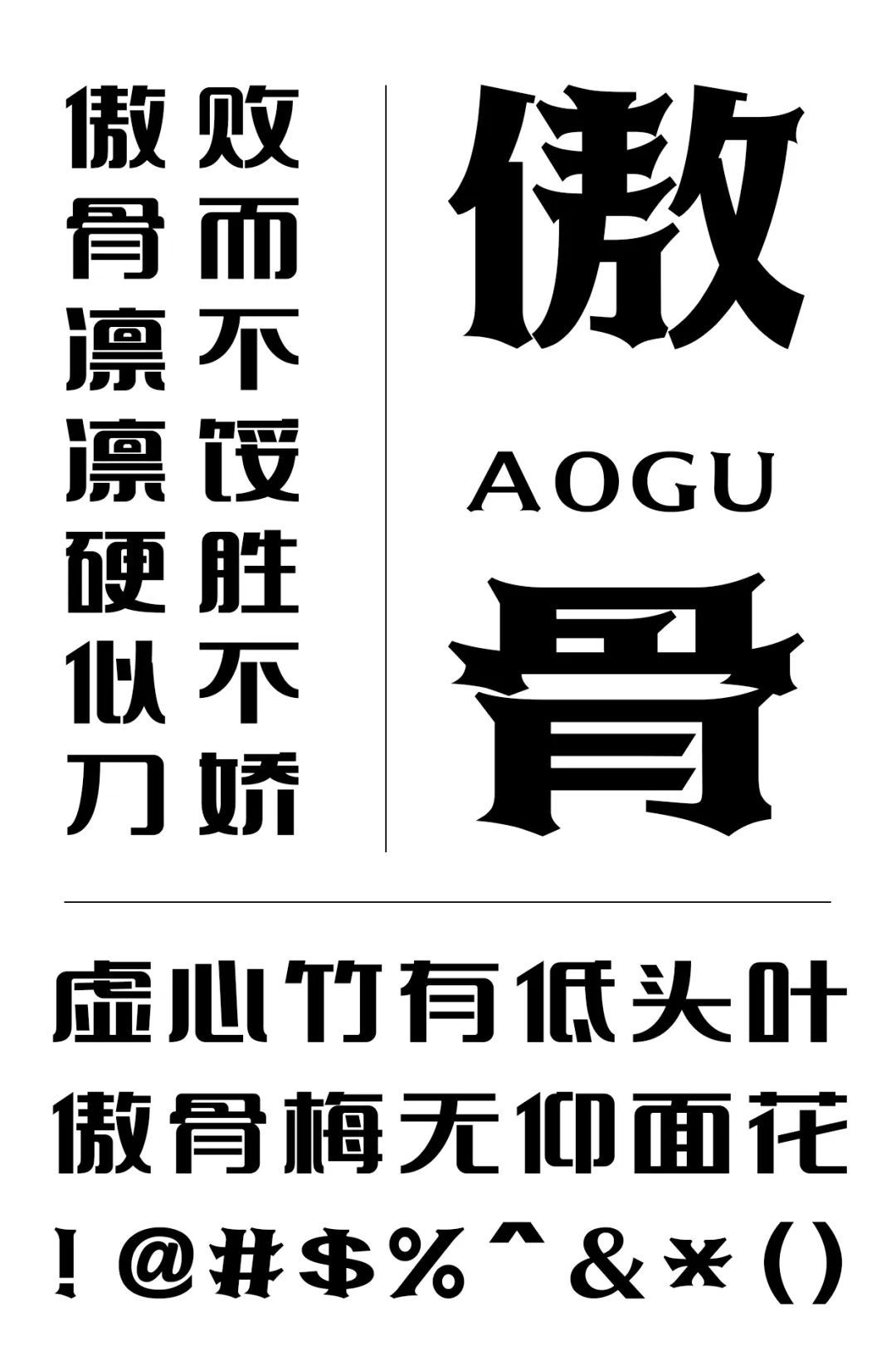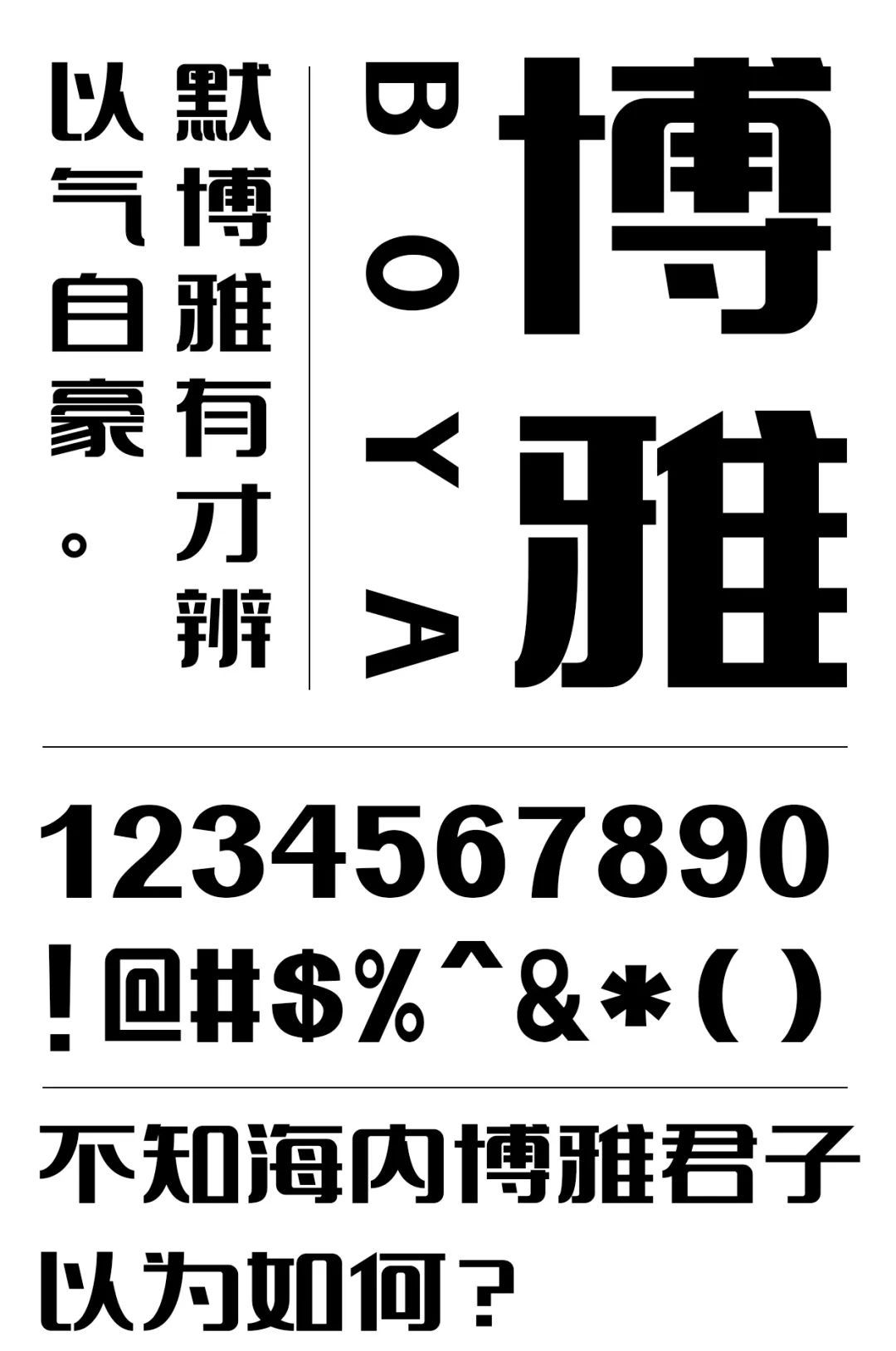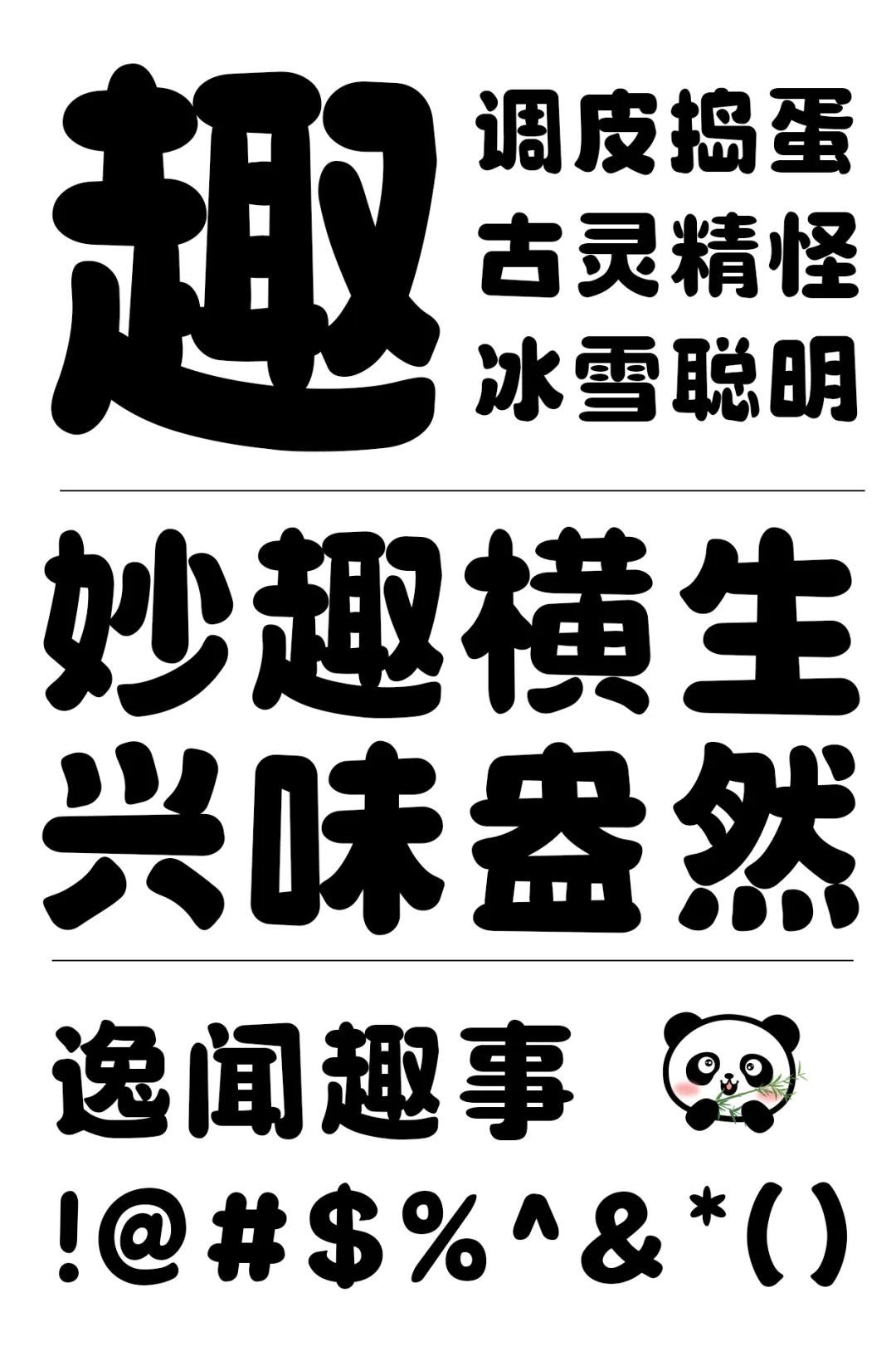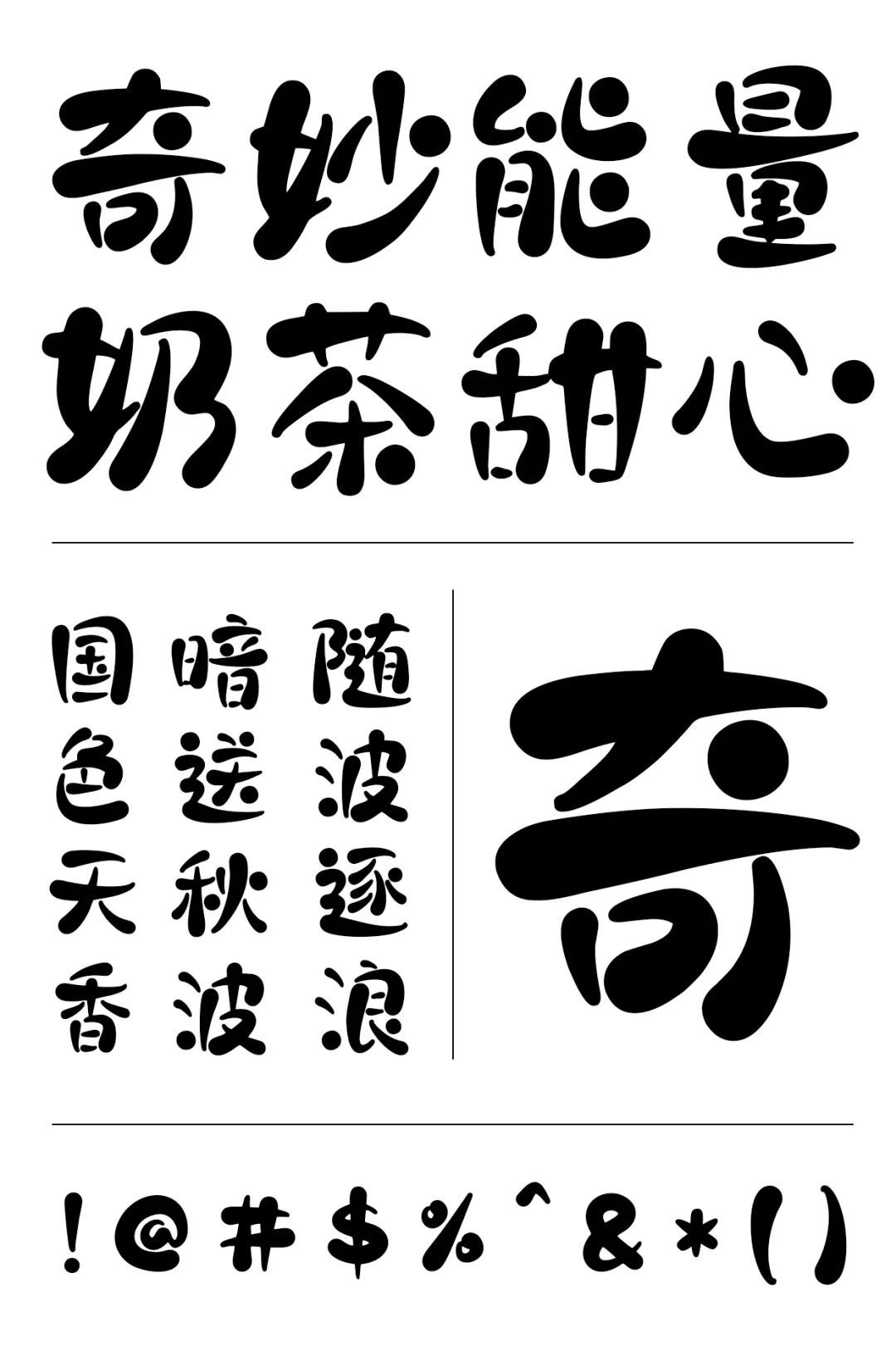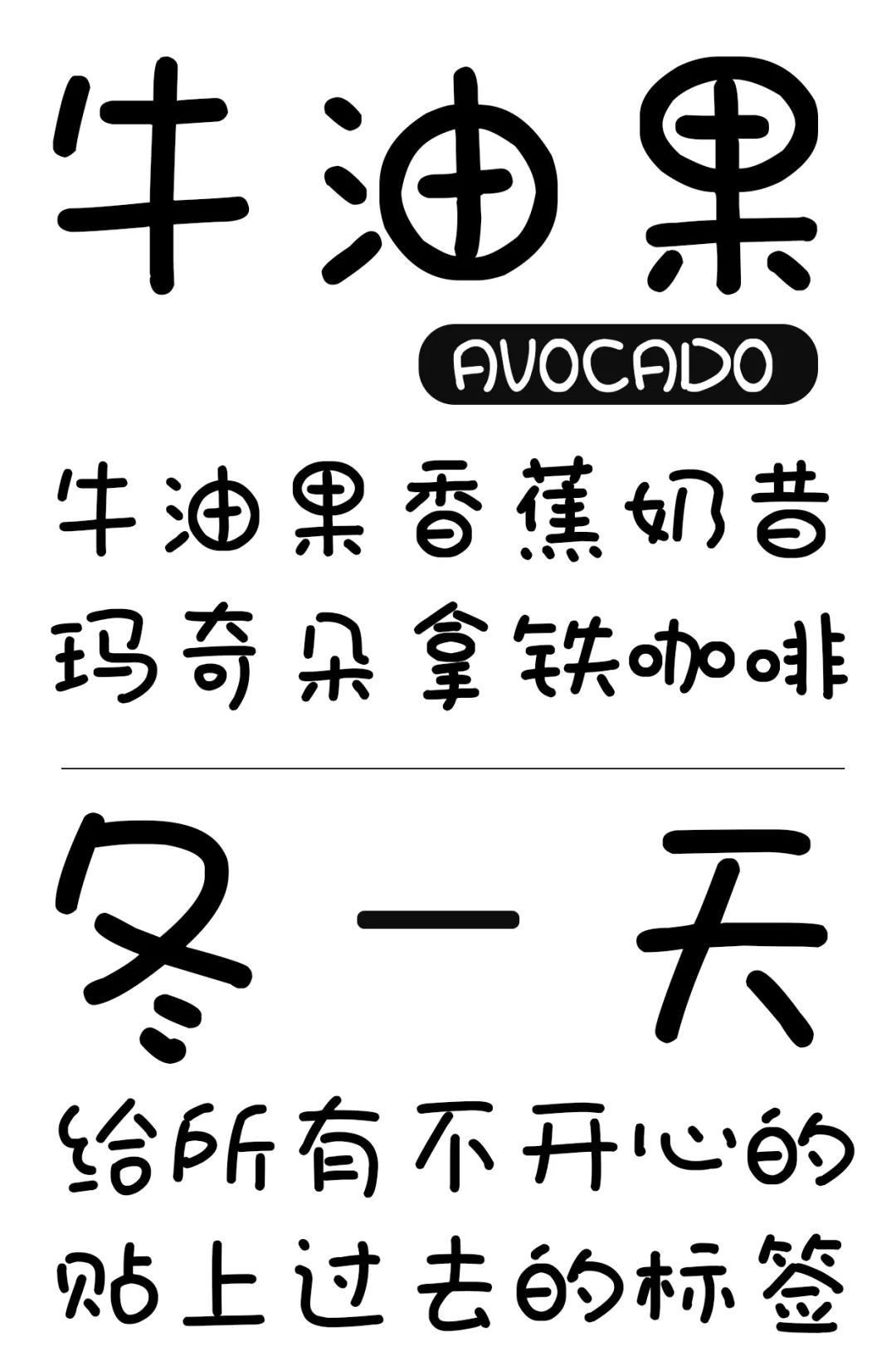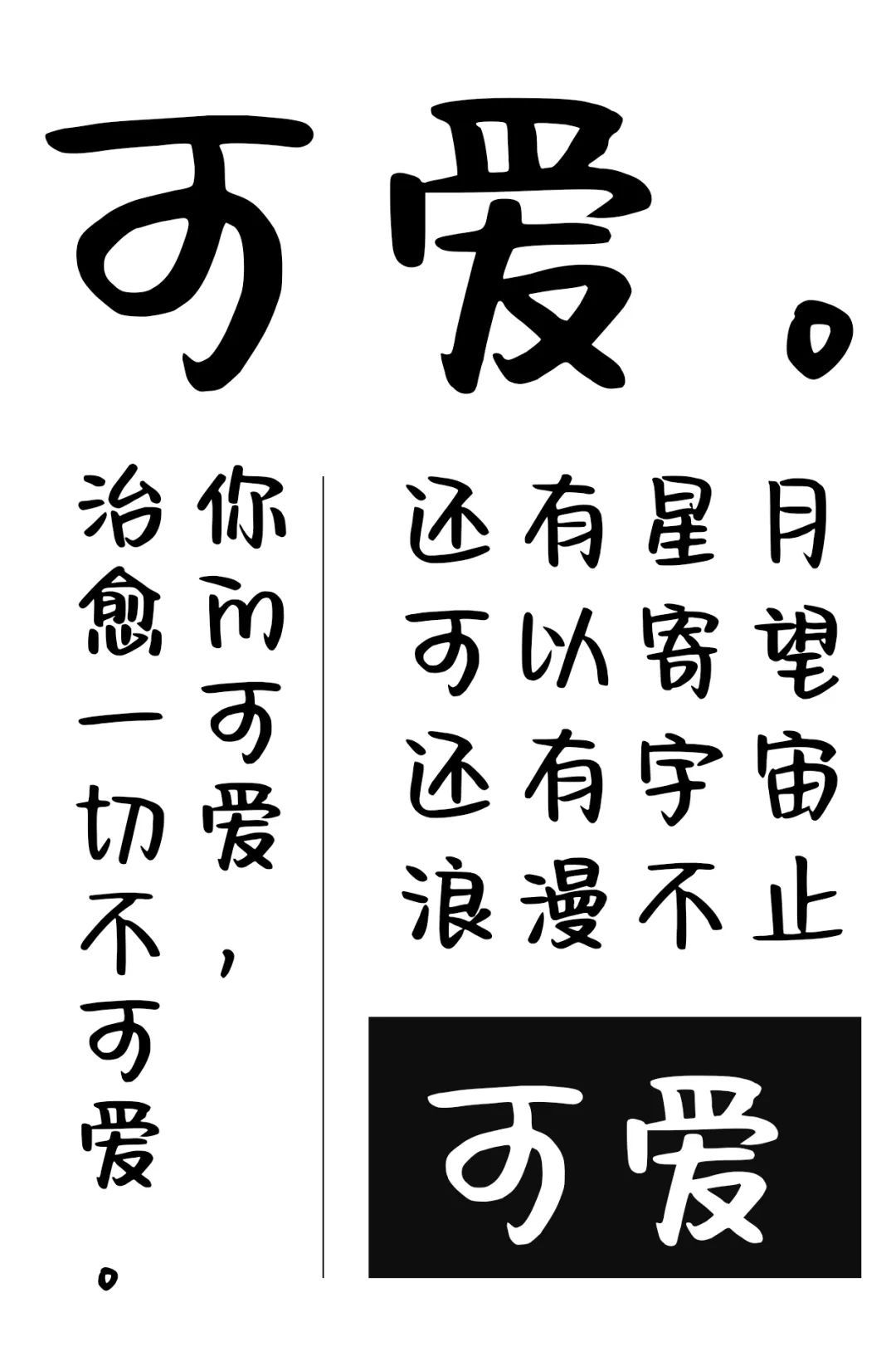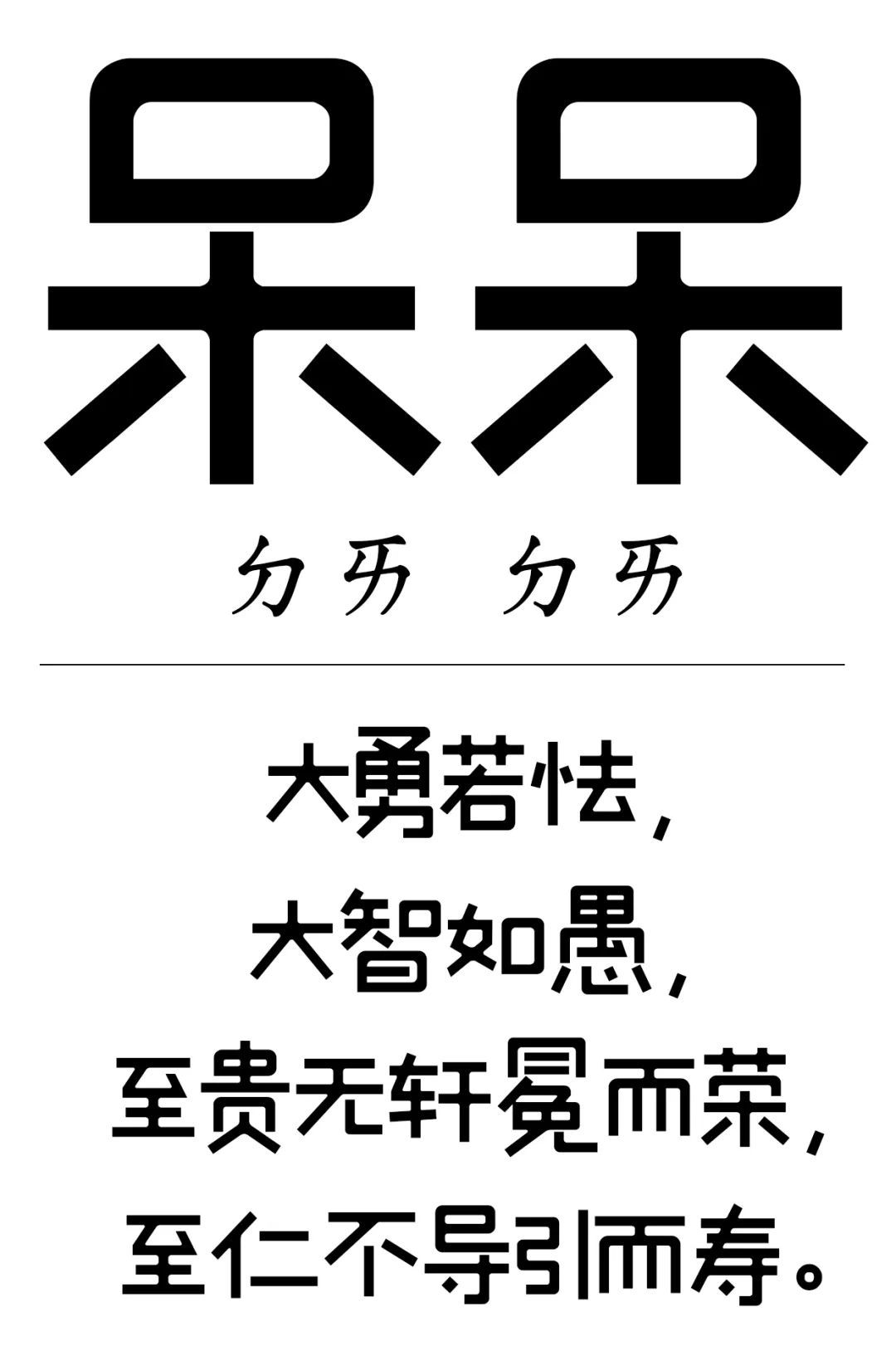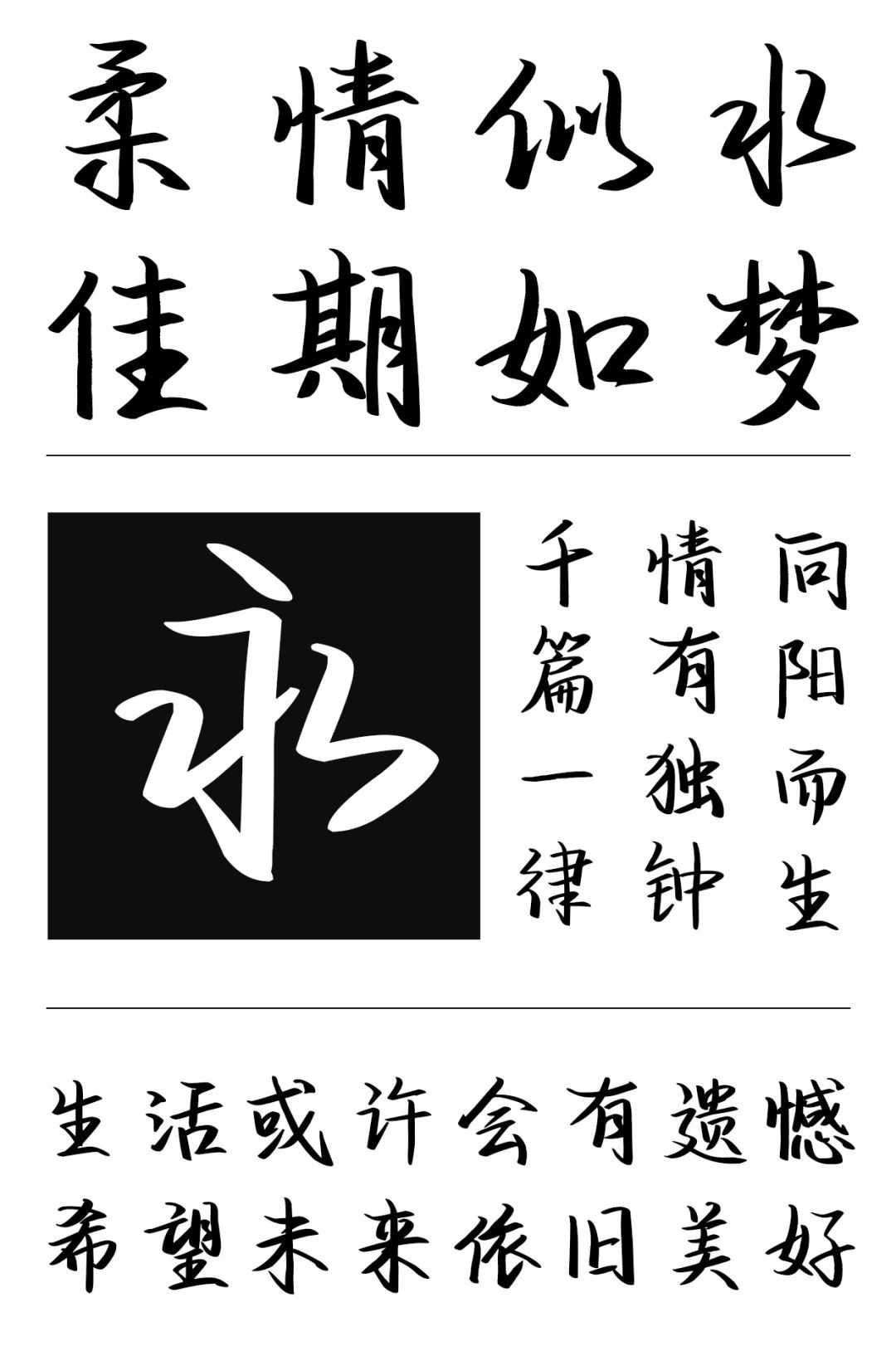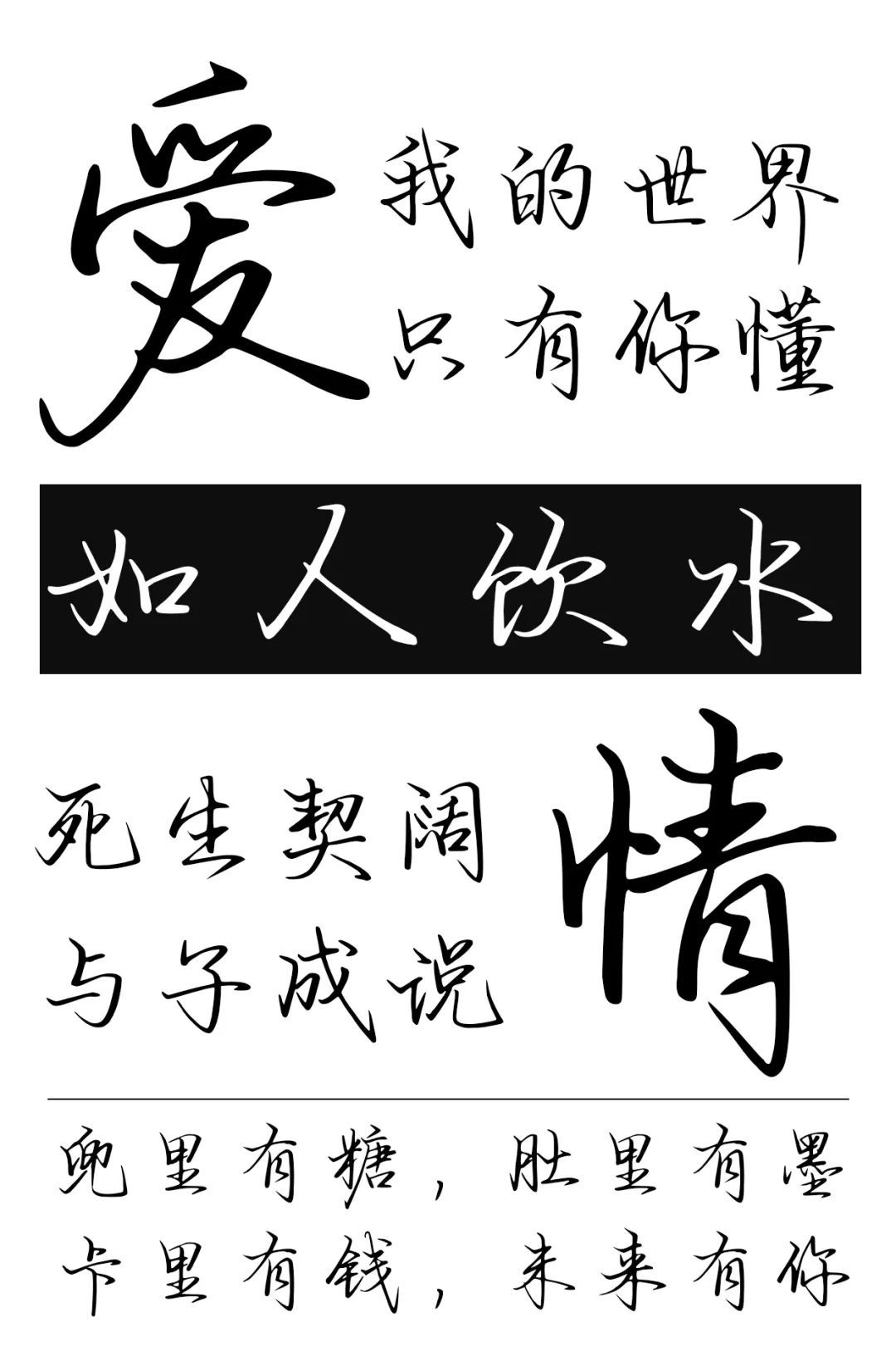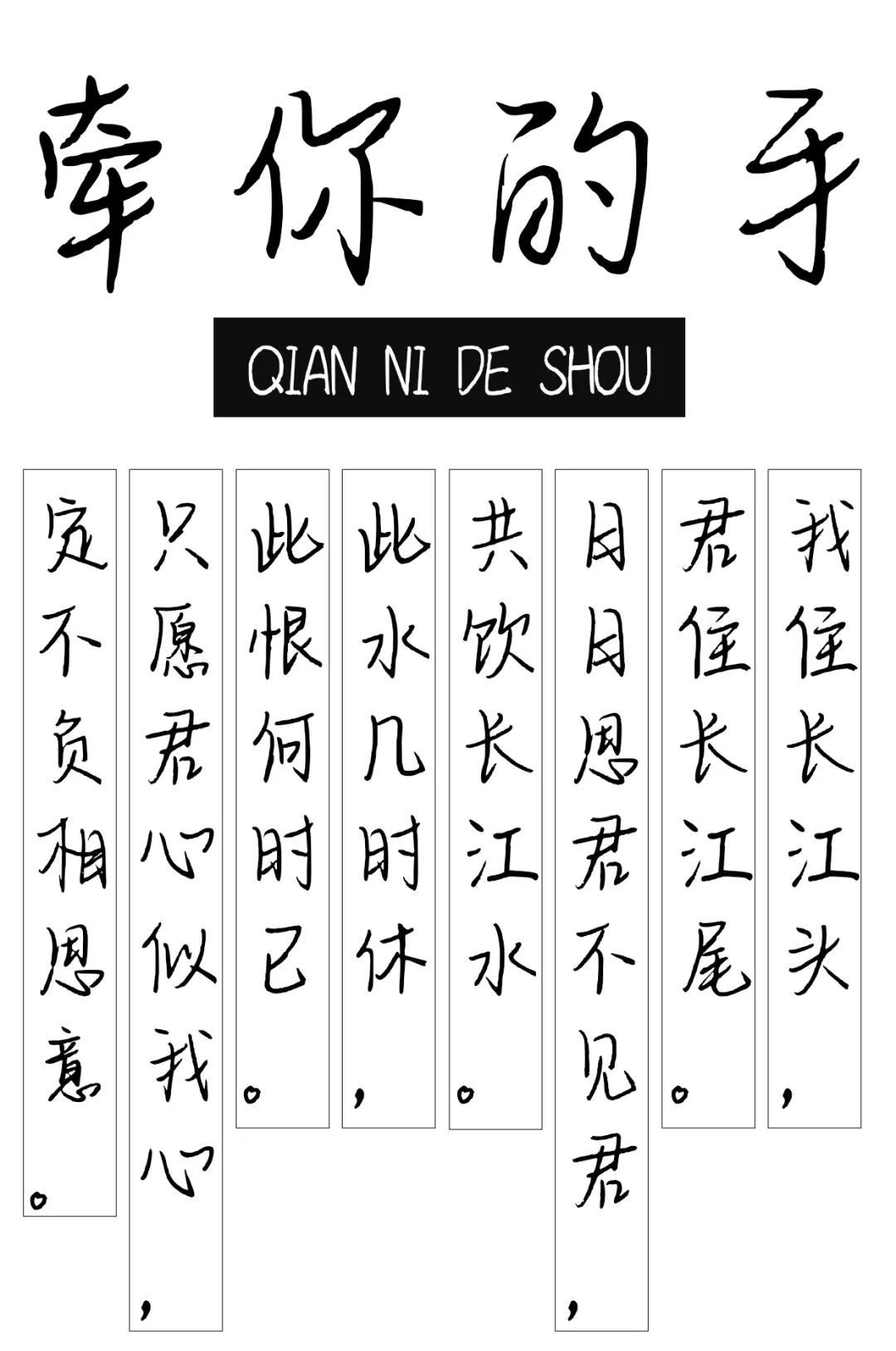
1、上首傲骨体
硬朗的线条之间的粗细变化不一,更显字形轮廓感。字体整体风格颇有文人傲骨风范。
2、上首博雅体
上首博雅体,字体笔画端正。博雅顾名思义笔画大气字体端正富有内涵,结字方正,气息儒雅,整体风格博学大气。
3、萌趣体
萌趣体这款字能在趣味、活泼、可爱、萌趣中体现,粗黑为字形基础,不规则的笔画,在排版时能表现趣味的节奏感。
4、上首波波手写体
上首波波手写体,以一端粗一端细的圆润的笔画和圆点书写,笔画整体浑圆,柔和、可爱,像果冻,像水滴,像中文感叹号,给人以温柔、俏皮、波动,胖乎乎、萌萌哒的感觉。
5、牛油果味的冬天
牛油果味的冬天,粗细的笔画加上圆体的设计风格,可爱又非稚嫩的气质凸显而出。
6、可爱的软糖奶酪
可爱的软糖奶酪这款字体富有意趣的笔画,简单清晰的结构,可爱的气质拿捏的恰到好处十分适合软萌妹子,萌萌哒的奶酪体让你每天都有萌萌的心情。
7、上首呆呆体
上首呆呆体,字体笔画均匀,横竖粗细一致,字型圆润,具有卡通动漫的风格。
8、千篇一律的温柔
千篇一律的温柔这是一款十分飘逸清新的字体,笔画给人舒适的感觉,没有尖酸刻薄的锐气,只有生动活泼的朝气。
9、听晚风将爱情吹散
听晚风将爱情吹散这款字体端正平直,行笔收缩自如,连笔自然,有着行云流水般手写风。
10、牵着你的手不放开
牵着你的手不放开字体字型凸显了青春的气息,无论是笔画还是笔触都搭配的十分合理。